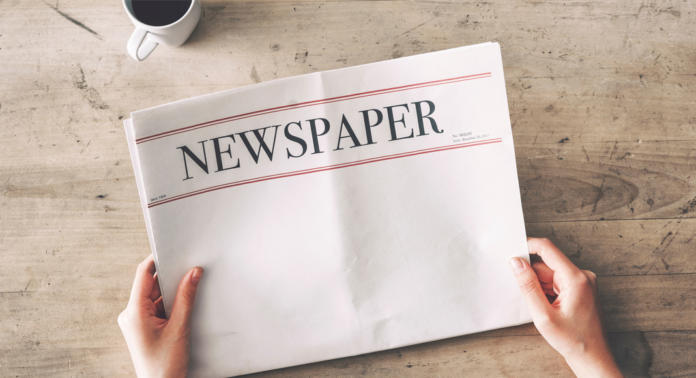
Die Schriftart Zeitung an sich gibt es natürlich nicht. Sehr wohl entsteht dazu meistens gleich ein Bild im Kopf: von dicken plakativen Headlines, von Zeitungsnamen in gebrochener Schrift oder langen Fließtexten mit Serifen. Ist alles richtig, schließlich finden sich in jeder Zeitung verschiedene Schriftarten.
Times – der Klassiker
Die namengebende britische The Times verwendet inzwischen längst modernere Varianten ihrer 1931 entwickelten Schrift, der Times New Roman. Da diese zu den Standardschriften zählt, entfacht sie in der Regel heute keine Begeisterungsstürme mehr.
Doch auch wenn sie noch so abgedroschen ist, vermittelt sie doch unbeirrt den Eindruck eines Zeitungsfließtextes. Wer sich dennoch etwas Abwechslung wünscht, findet zahlreiche kostenlose Alternativen dazu, unter anderem in unserem Artikel Times-New-Roman-Alternative: Berühmte Zeitungsfonts zum Download.
Schriftart Zeitung – mit Serifen oder ohne?
In den allermeisten Zeitungen erscheinen beide Formen. Die Fließtexte sind zwecks besserer Lesbarkeit normalerweise in Serifenschriften gedruckt. Headlines finden sich sowohl mit als auch ohne Serifen. Subheadlines und Vortexte bestehen hingegen als Kontrast häufig aus serifenlosen Fonts. Der Zeitungsname glänzt oft – zumindest bei tradtionellen Blättern in einer gebrochenen Schrift.
Welche Schriftarten Sie für Ihr Projekt benötigen, hängt davon ab, ob Sie eine komplette Zeitung nachbilden oder lediglich eine knackige Schlagzeile produzieren wollen. Wenn Sie auf verschiedene Schriftarten setzen, sollten diese unbedingt miteinander harmonieren.
Typische Beispiele für Schriftart Zeitung
Große Zeitungen verwenden oft eigene Weiterentwicklungen, um sich von der stetig wachsenen Konkurrenz auch im Internet abzusetzen. Als Basis für diese individuellen Schriften dienen alte Bekannte, die sich deshalb auch für eine Zeitungsimitation eignen. Dazu zählen unter anderem die Helvetica (s. dazu auch Helvetica – Alternativen zum Typo-Klassiker), Franklin Gothic, Bodoni, Garamond, Times New Roman, Centura, Concorde und Excelsior.
Schriftart Zeitung – kommerziell nutzbar und gratis
Die großen Tageszeitungen haben überwiegend eigene Fonts entwickeln lassen. So kreativ müssen wir glücklicherweise nicht sein. Schließlich geht es vor allem darum, den Zeitungscharakter aufleben zu lassen.
Gebrochene Schriften
So manches Tagblatt sowie der eine oder andere Bote trägt seinen Namen stolz in einer gebrochenen Schrift zur Schau. Verbunden mit entsprechenden Schlagwörtern wird hier sofort die Assoziation zu einer Zeitung hergestellt.
Chomsky
Der Font erinnert stark an den Schriftzug der New York Times und wird deshalb international mit einer Zeitung in Verbindung gebracht.
Klaber Fraktur
Eine Frakturschrift vom Spezialisten Peter Wiegel. Mehr Beispiele zu dieser Schriftfamilie stellen wir Ihnen auch unter Frakturschrift – der besondere Hingucker vor.
Schriftart Zeitung mit Serifen
Für Fließtexte sind Serifenschriften einfach die beste Wahl, weil diese am angenehmsten und schonendsten für die Augen sind. Es kommen aber auch Headlines groß damit heraus.
Antic Didone
Der Font aus Mexiko wirkt gleichermaßen antik wie modern. Enwickelt für Schlagzeilen, gibt es Antic Didone auch in einer Sans- und einer Slab-Version. Wer verschiedene Schriften nutzen möchte, hat hier also gleich eine harmonische Kombination.
Brawler
Die kompakte und robuste Brawler wurde zunächst für Zeitungen konzipiert und eignet sich auch sehr gut für kleine Schriftgrößen.
Belgrano
Für sehr kleine Schriften ist auch Belgrano eine gute Wahl. Ursprünglich für Zeitungen entwickelt, haben die Designer aus Chile diesen Font auch für Internetseiten optimiert.